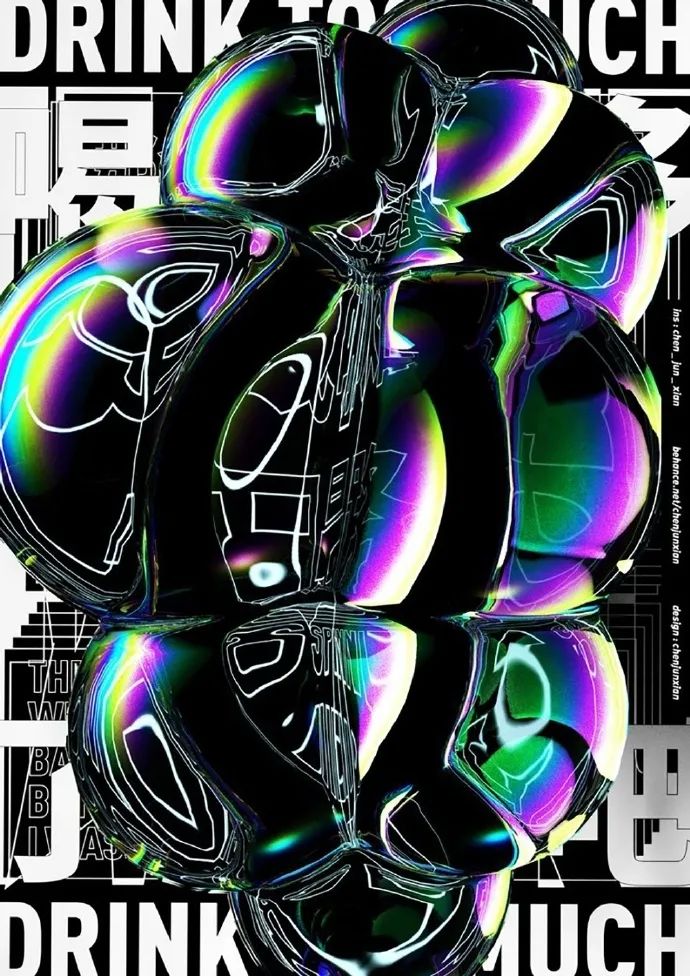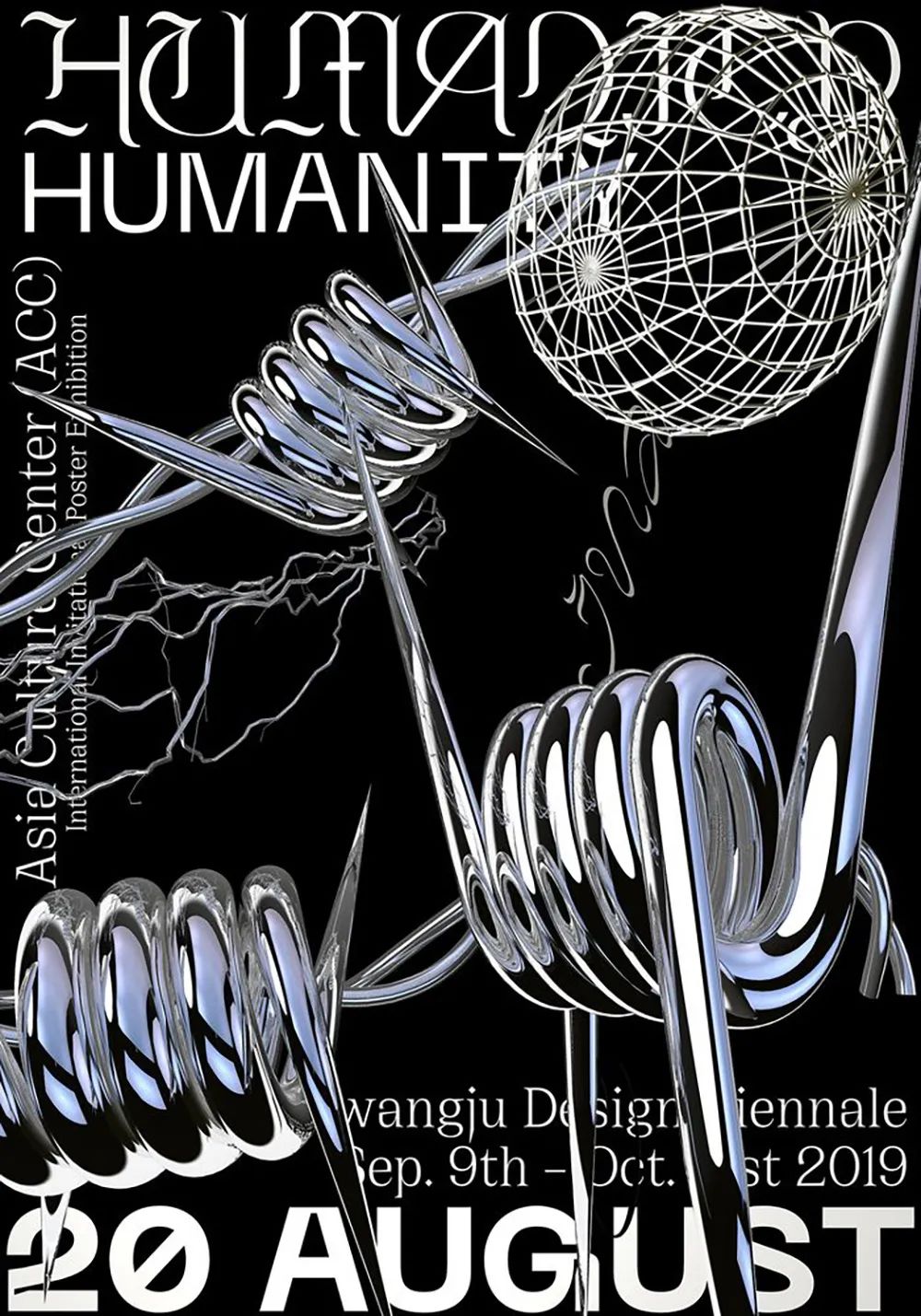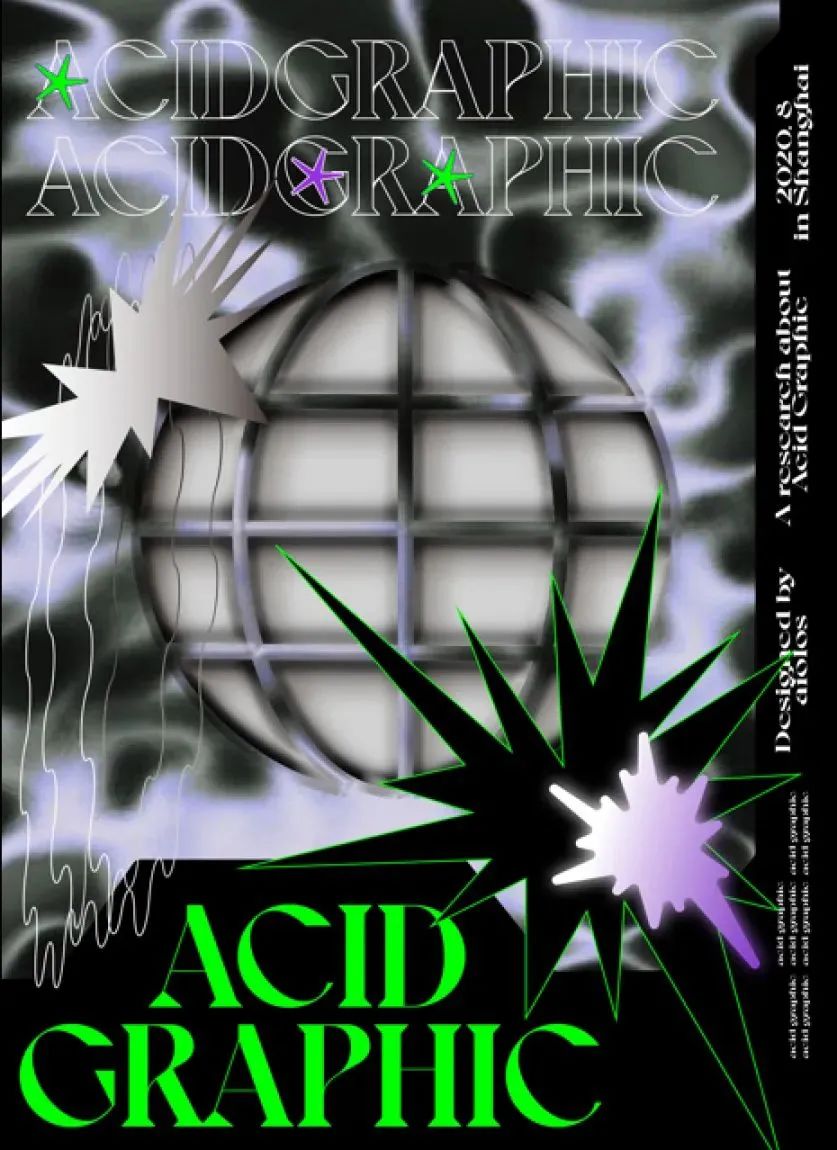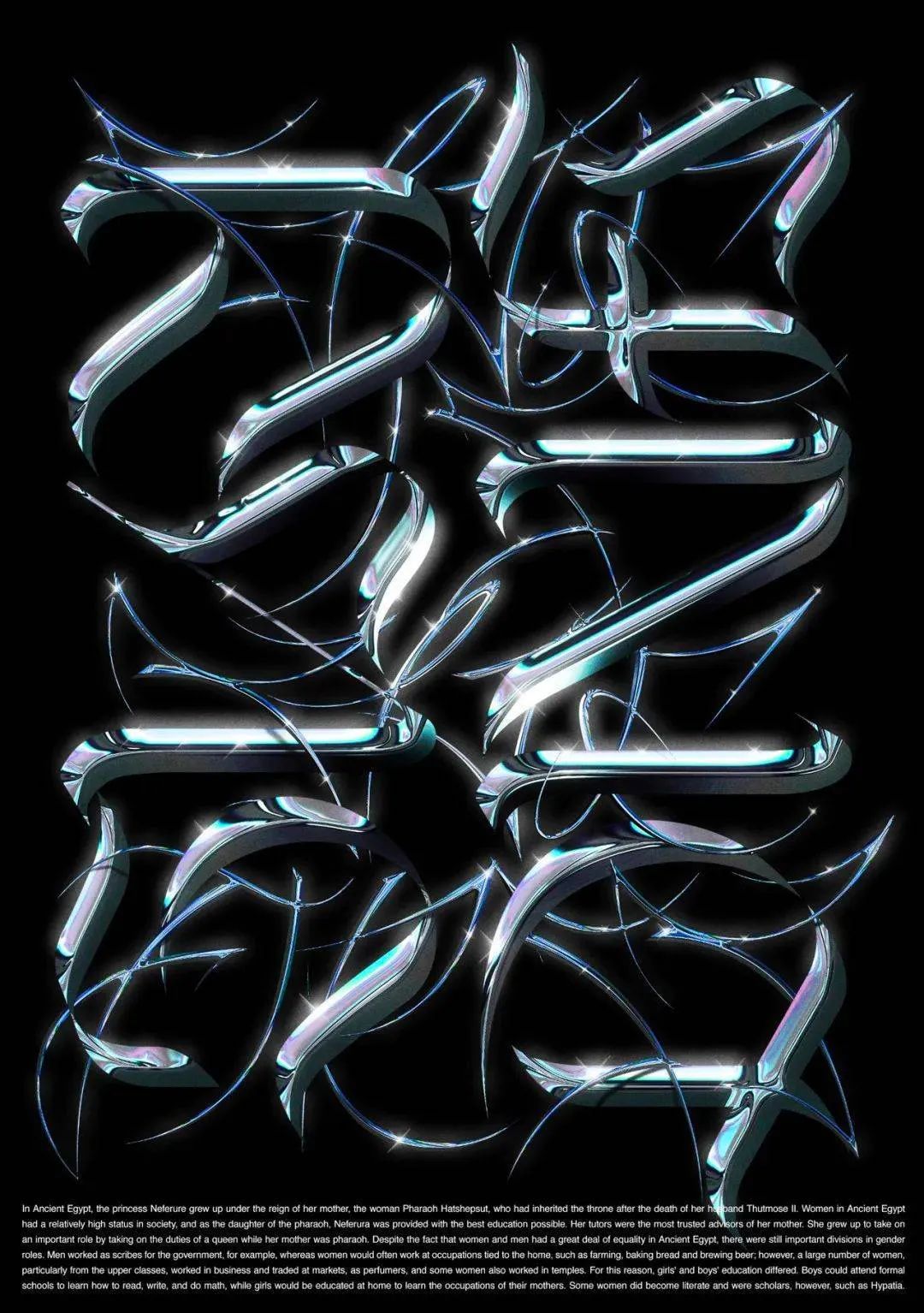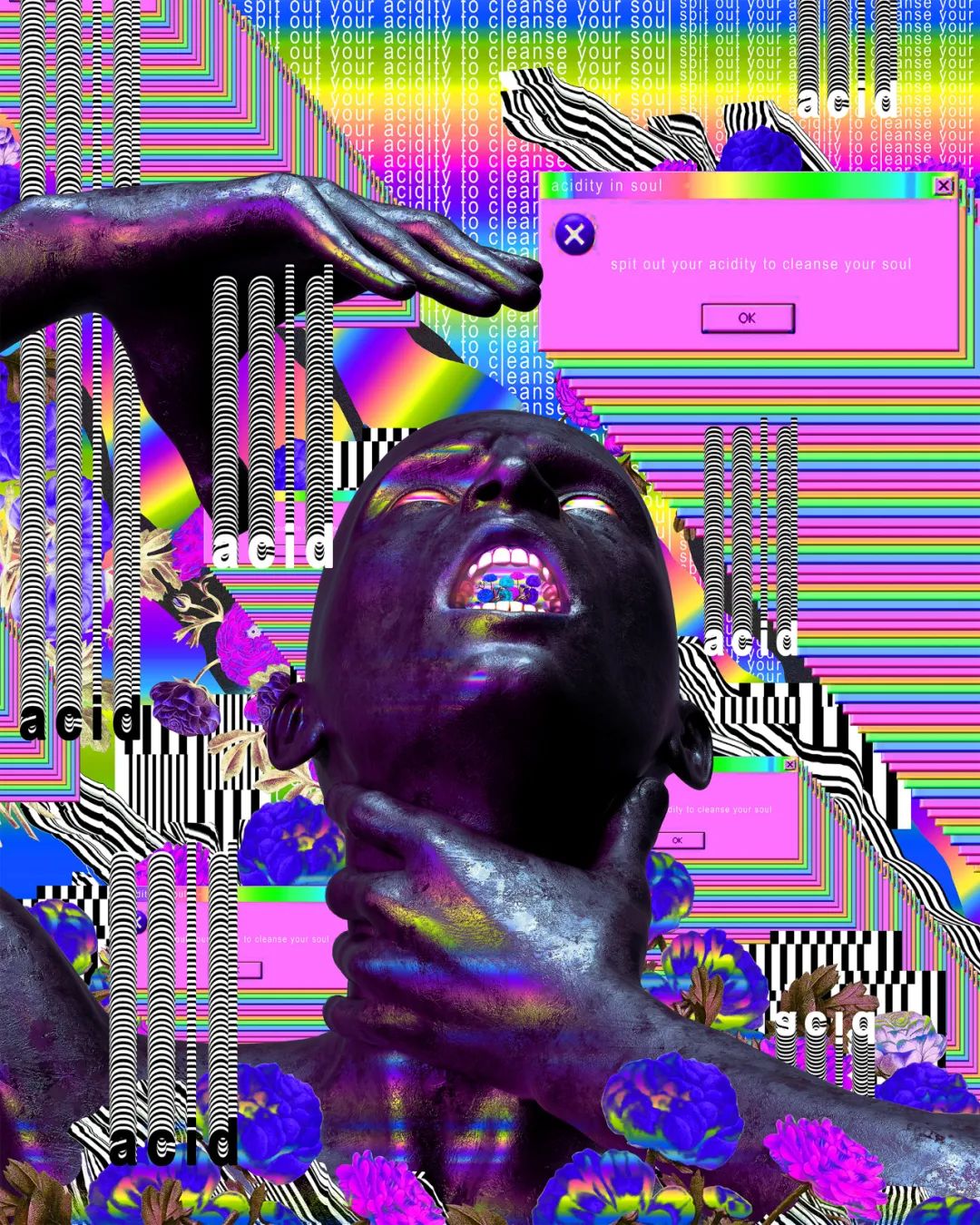
爆火的“酸性设计”分享,我给你做了N套特效,速拿去用~
最开始听到“酸性设计”这个词的时候,柚子满脑子想的都是:
划掉划掉,当然不是!
“酸性设计”一词是由Acid Graphics翻译来的,其中“Acid”有迷幻的意思。所以总的来说Acid Graphics实际上就是一种迷幻风格的设计,起源于上世纪90年代的酸浩室音乐(Acid House),电子舞曲以及嬉皮士文化,带有强烈的愤世妒俗的感觉。
快和柚子一起看看什么才是真正的“酸性设计”~
在这些作品中,整个画面混乱又统一,复古又科技,五彩斑斓又暗黑,总的来说就是一种矛盾的迷幻感。
荷兰创意机构G2K的艺术总监Rudmer van Hulzen曾说:“酸性设计”的核心是挑战传统对美感和欲望的定义。
从蒸汽波到赛博朋克再到酸性设计,音乐风格对设计风格的创新影响深远,这大概就印证了那句话——艺术都是相通的。
“酸性设计”风格中常见的元素是3D物体,荧光色和渐变,欧普图案还有金属字体,那这些都怎么实现呢?
水银质感太棒了~
五彩斑斓的金属和酸性艺术🔐死
透明字体丰富材质,不可或缺哦~
✨blingbling的硬合金字体超级好用✨
柚子不光为大家准备了字体特效,还为大家搜集了不少适合“酸性设计”的字体,下面换给大家看看~
有了这些字体特效,柚子轻轻松松就能做出一张时下最流行的“酸性设计”海报还不动心吗,感觉掌握了财富密码😊